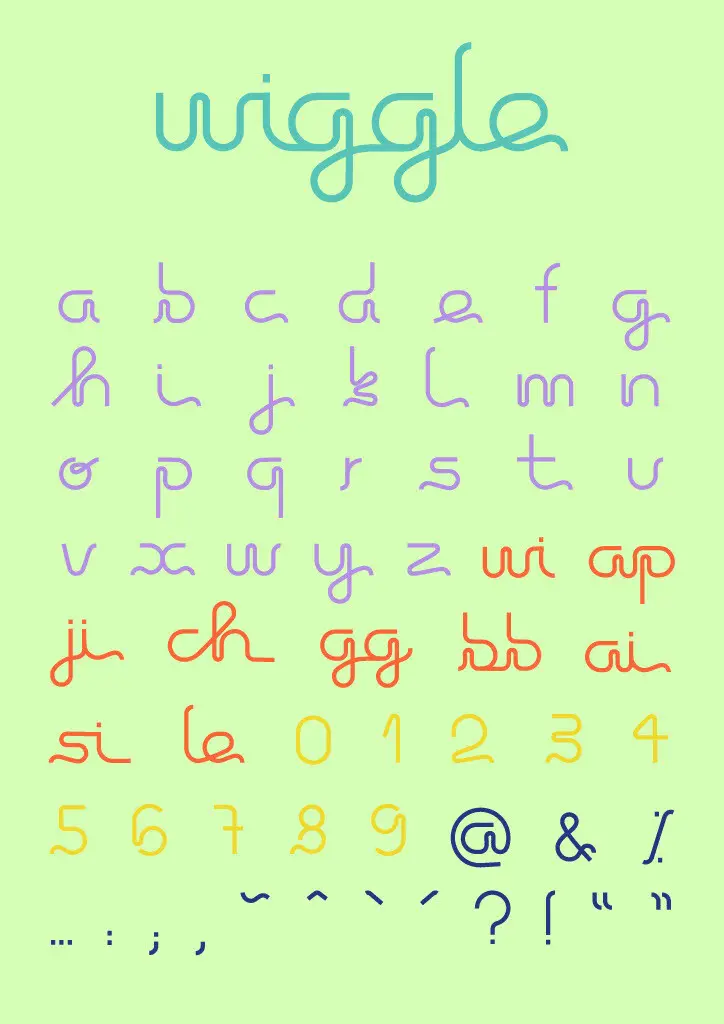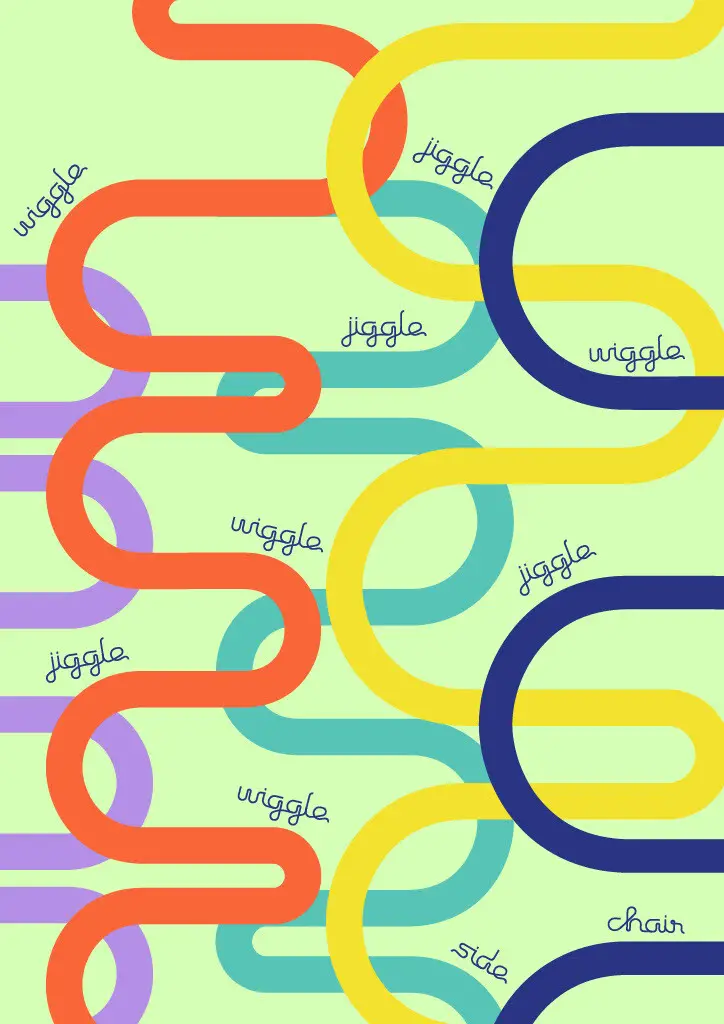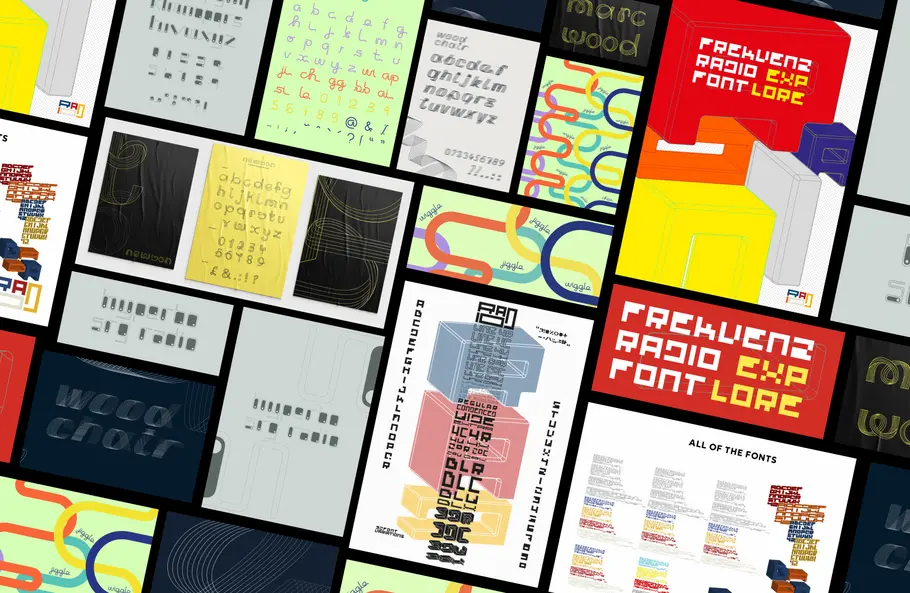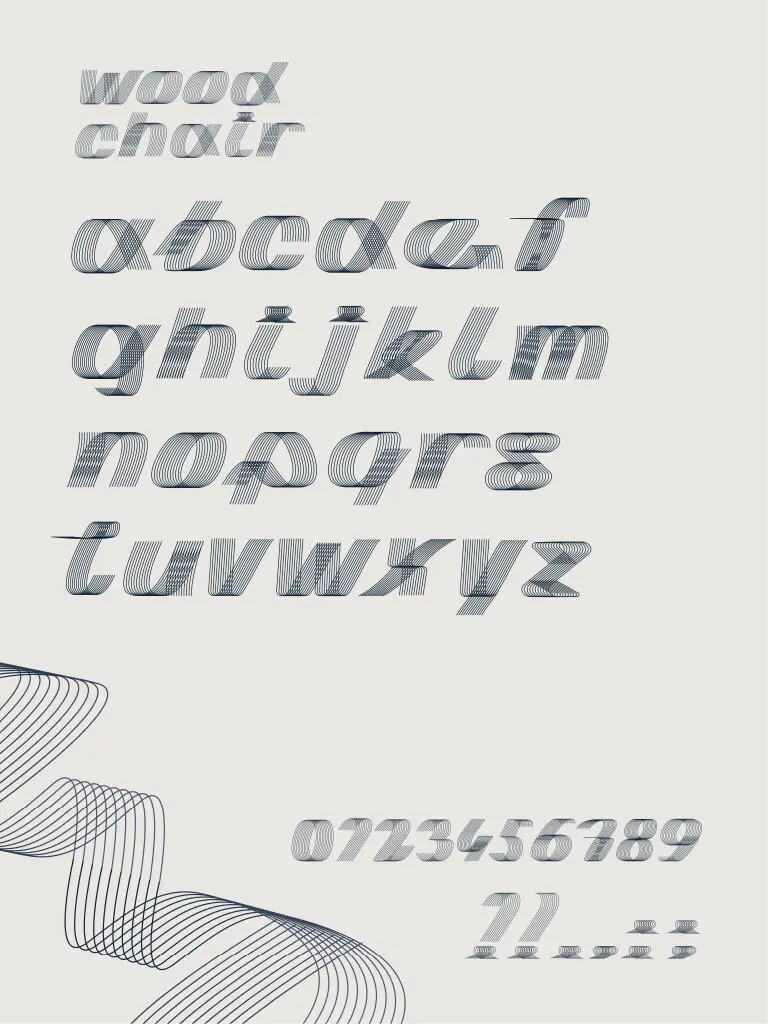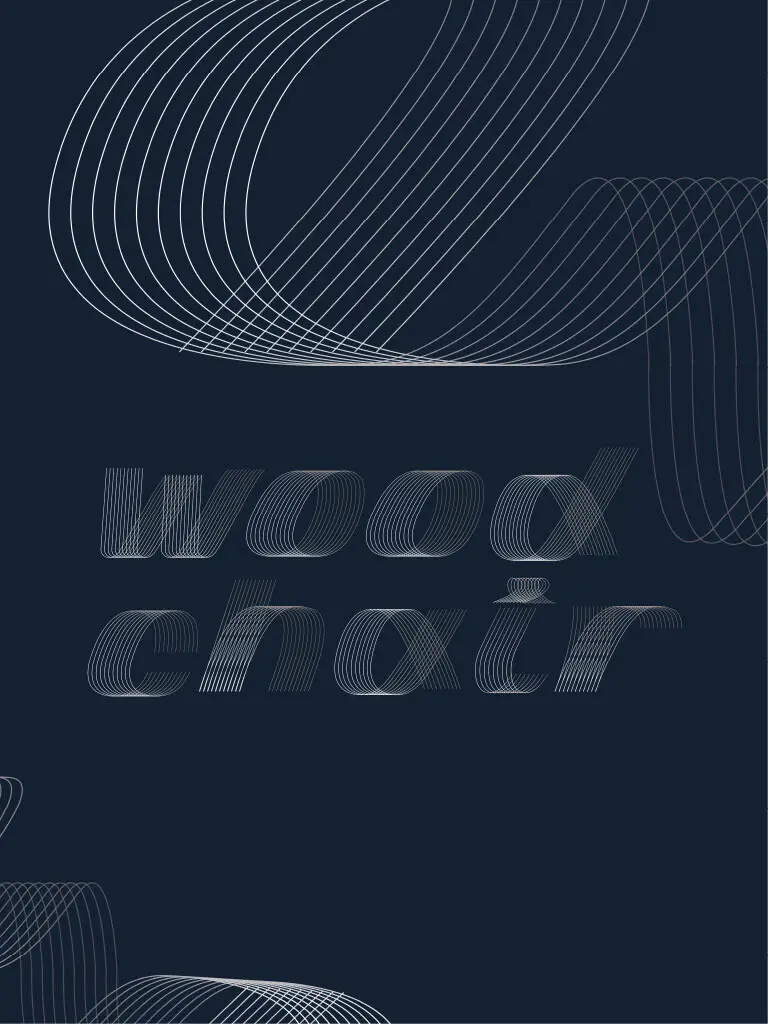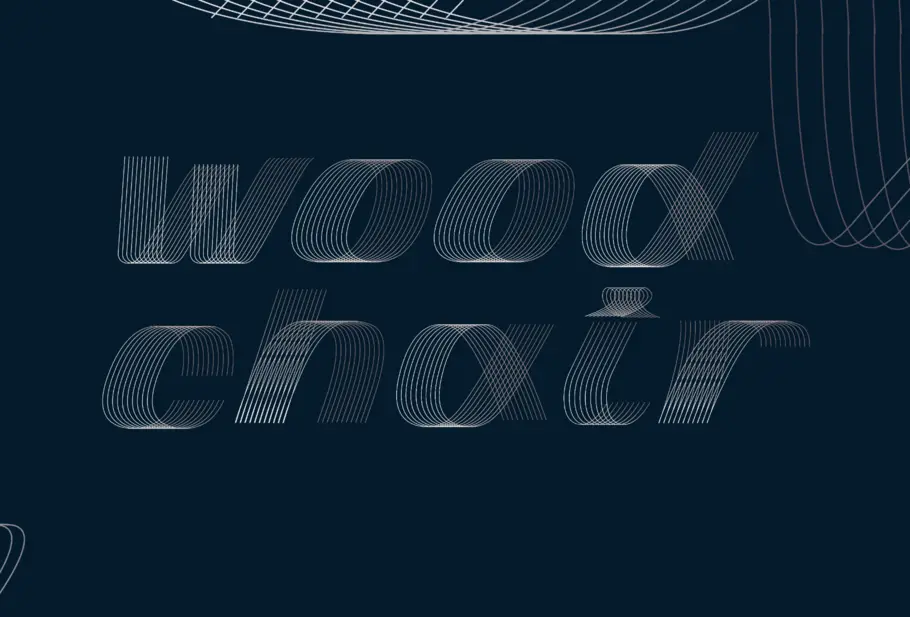
Monotype x Middlesex.
É com admiração que observamos o trabalho dos estudantes. Geralmente nos surpreendemos com as soluções tipográficas que esse novo olhar oferece. Com ideias fortes, inspiração genuína e orientação, podemos ter projetos promissores.
Emilios Theofanous, Designer de fontes na Monotype.
Este ano, tivemos a felicidade de colaborar com a Middlesex University e com o módulo tipográfico de Andy Gossett. Phil Garnham (Diretor Criativo de Tipografia e ex-aluno da Middlesex) e Emilios Theofanous (Designer de fontes da Monotype) tiveram a oportunidade de realizar duas sessões online, inicialmente para ajudar a dar o pontapé inicial no projeto e uma sessão posterior durante o semestre para discutir o processo, analisar os designs e responder a perguntas relacionadas a design de fontes.
Criar uma fonte durante um semestre acadêmico não é uma tarefa fácil, especialmente neste ano que passou, em que tivemos sessões online e interações diárias limitadas entre os estudantes. Então, é com admiração que sempre observamos o trabalho dos estudantes e, geralmente, somos surpreendidos pelas soluções tipográficas que esse novo olhar oferece. Nem tudo funciona imediatamente em um ambiente comercial, mas com ideias fortes, inspiração genuína e orientação, podemos ter projetos promissores. Os estudantes do terceiro ano do bacharelado de design gráfico não foram exceção neste ano. Eles se esforçaram muito, entraram de cabeça neste novo projeto com curiosidade e mostraram que estavam prontos para experimentar e explorar o incrível mundo da criação de fontes.
Durante a primeira sessão online, vimos os princípios básicos do design de fontes, as tendências tipográficas atuais e exploramos o briefing criativo.
O briefing criativo:
Os estudantes precisavam escolher um objeto de uma seleção de designs icônicos de produtos (como móveis, maquinário, utensílios, eletrodomésticos) e desenvolver uma nova marca tipográfica para eles. O objetivo era ampliar as ideias iniciais para um design da fonte totalmente funcional.
Workshop conceitual:
Após algumas semanas, nos reunimos novamente para discutir o progresso. Foi muito interessante ver como os estudantes transformaram suas inspirações em formas tipográficas. Muitas delas eram traduções ilustrativas muito literais e outras muito modulares e, muitas vezes, ilegíveis. É importante entender o contexto dessas propostas iniciais. Como parte da identidade de marca, o contexto pode orientar o gênero da tipografia de display e passar pelo design gráfico. Então, o feedback que demos serviu para orientar o estudante sobre como ampliar suas ideias para transformá-las em fontes prontas que podem ser usadas por marcas no mundo todo. Falamos sobre a importância da legibilidade, por exemplo, o que devemos considerar ao basear uma fonte em um logotipo e como a coerência entre formas tipográficas semelhantes pode ser a chave para um ritmo harmônico e tipográfico. Alguns dos designs eram modelos que se baseavam em formas estruturais sem muito peso. Então, falamos sobre a ideia de peso e escala, além da função do tamanho da fonte, os cenários em que a fonte será usada, como deve ser a aparência quando ela for impressa ou exibida em mídias diferentes.
As fontes:
Durante outras três semanas, sob a orientação de Andy Gossett, os estudantes transformaram seu conceito em letras do alfabeto de A a Z, números e pontuação básica. Cada fonte foi enviada para revisão e, agora, podemos compartilhar algumas das favoritas